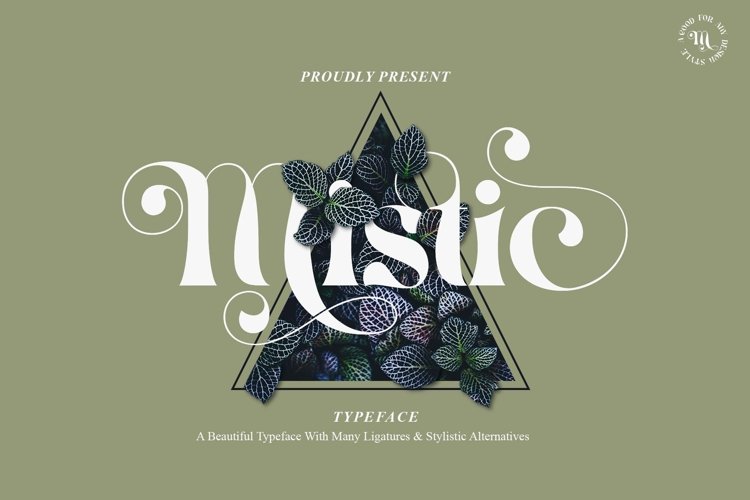
Fontbundles Mistic Font
[Fontbundles] Mistic Font
Современный шрифт Serif с поворотным чередованием, созданный в результате частого использования шрифта для свадебных нужд.
Этот шрифт имеет элегантную и смелую концепцию.
Он идеально подходит для дизайна с романтическими темами, такими как свадебные свойства, открытки Валентина, романтические цитаты и другие.